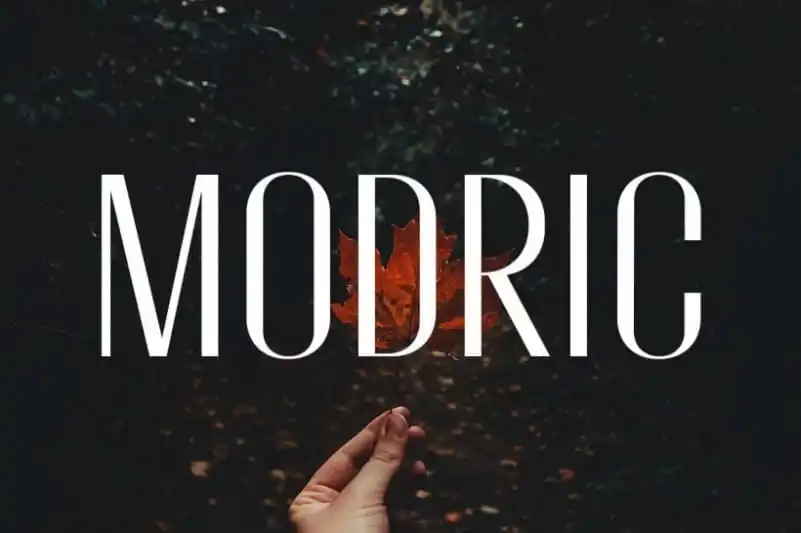
Introduzimos Modric Sans Serif Font, uma elegante fonte sem serif que se inspira na arte e no belo. Desenvolvida pelo designer Motokiwo no site 99designs, esta é uma font especialmente projetada para headlines, ideal para aplicativos empresariais, projetos de beleza, moda ou marca. Com seu formato condensado, Modric traz um toque de sofisticação perfeito para qualquer projeto. Sujeito a apreciar por suas qualidades legais e multilíngues, esta font em letras maiúsculas é uma escolha óbvia para qualquer aplicação que valorize elegância e simplicidade. Modric é certamente um recurso gráfico indispensável para criar identidades visuais impactantes para seus projetos de beleza, moda ou marca.